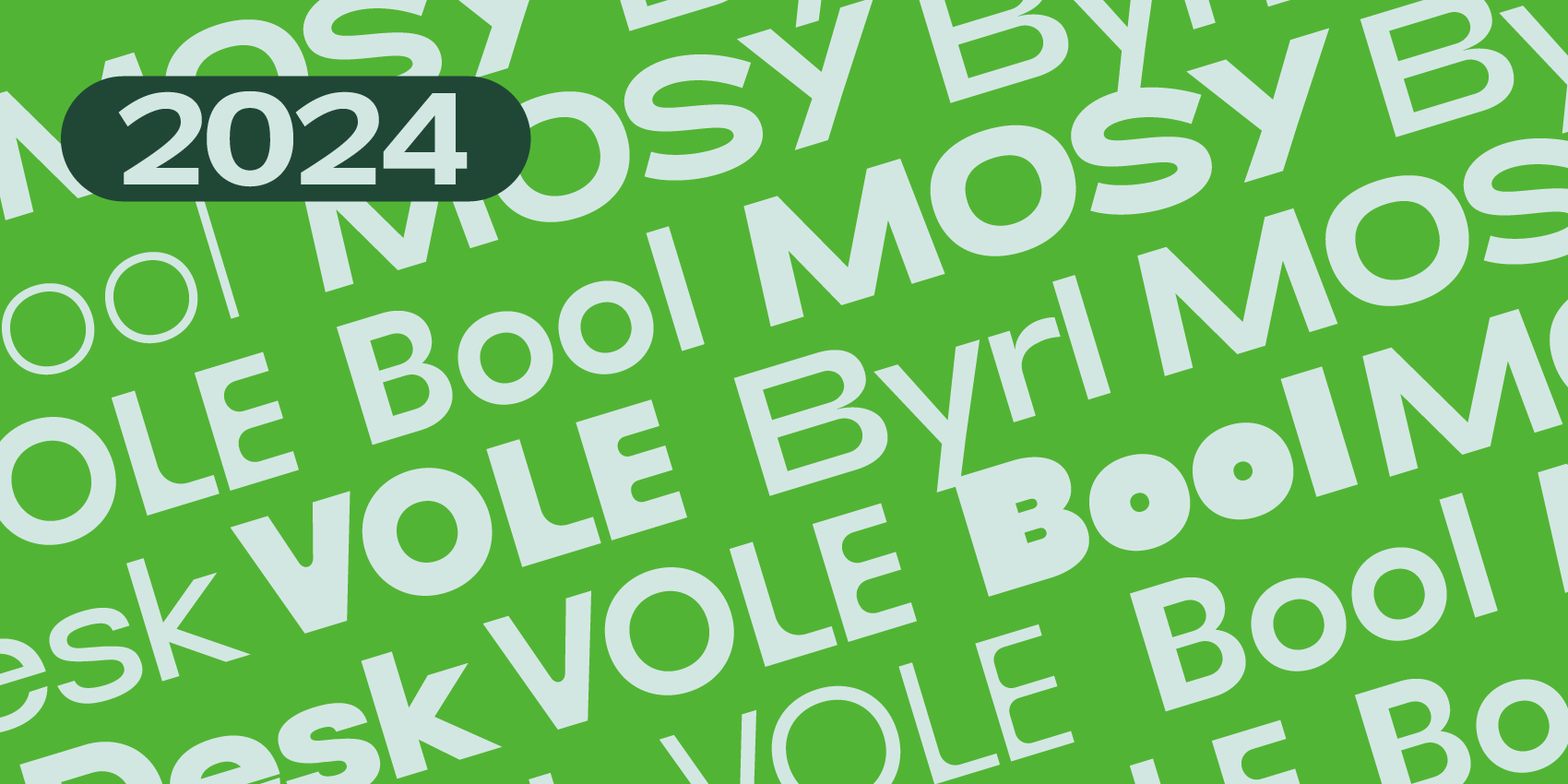
El auge de las fuentes sans-serif modernas en 2024: desde las sans simples hasta las elegantes
En 2024, las fuentes sans-serif modernas han pasado de ser minimalistas y prácticas a convertirse en una opción de estilo intencional. Las fuentes sans-serif, que no tienen los pequeños pies al final de las letras como las fuentes serif, son conocidas por su apariencia limpia y simple.
Lo que hace que las fuentes sans-serif sean modernas son características como un marco geométrico, un grosor de línea uniforme y detalles creativos que aportan personalidad: piense en letras con giros únicos como una letra S invertida o terminales extralargas (finales de un trazo) que llegan más lejos de lo habitual. Estas fuentes no solo se centran en la apariencia, sino en añadir carácter al texto.
Por otro lado, las fuentes sans-serif clásicas tienen un estilo más atemporal. Suelen ser un poco más estrechas y pueden mantener un aspecto más bien tradicional con un poco de contraste de líneas, especialmente cuando se trata de fuentes de texto.
Las fuentes retro siguen principios de diseño distintivos que prevalecen en esas épocas específicas. Por ejemplo, una fuente Bauhaus se simplifica y se construye a partir de formas geométricas. O bien, una tipografía Art Deco juega con el contraste de algunas letras que son geométricas y otras que son estrechas (condensadas). Las barras transversales pueden ser más altas o más bajas que en los diseños sans clásicos.
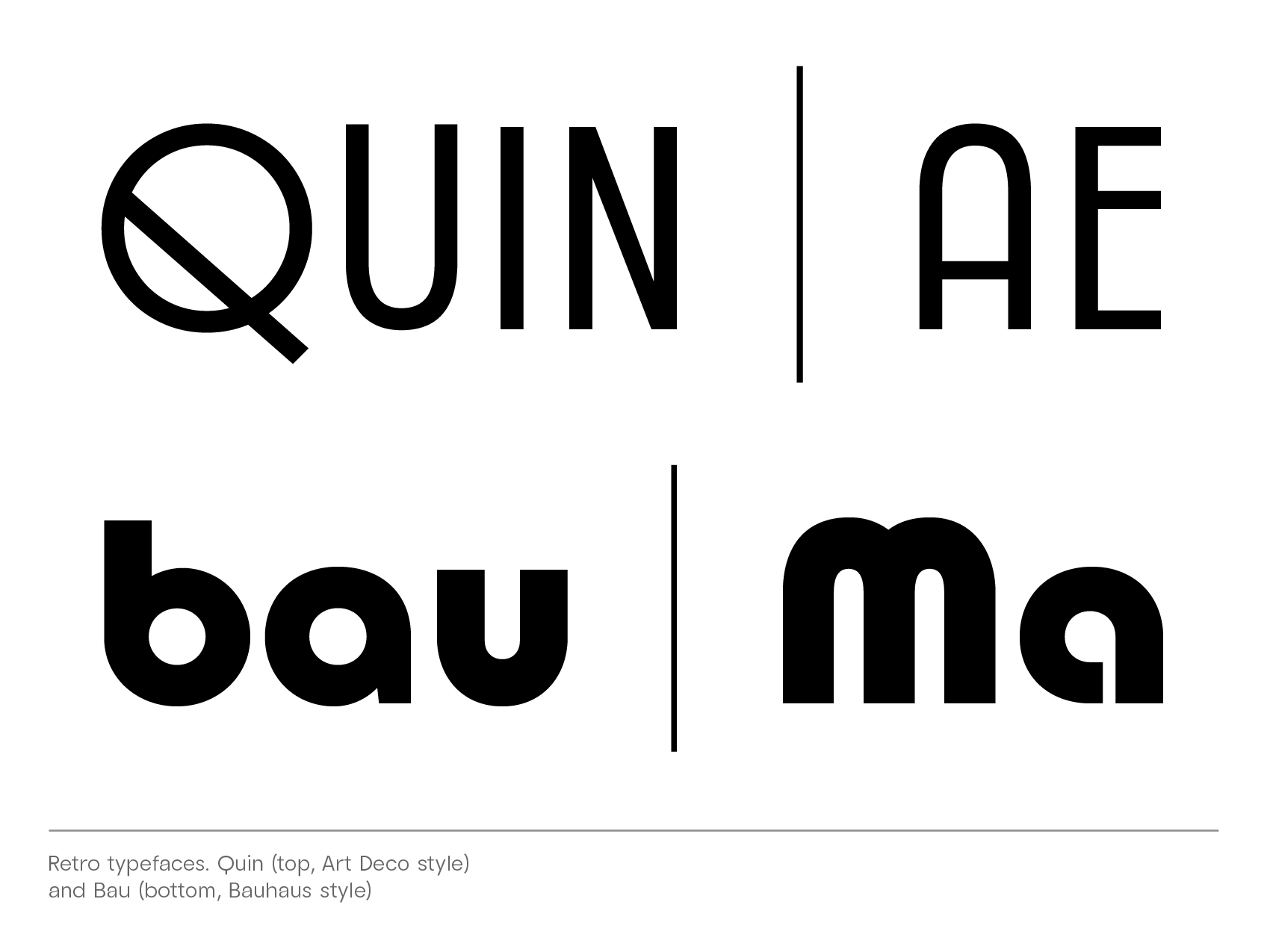
Si bien las fuentes sans-serif modernas llaman la atención ya sea por su enfoque minimalista o por su individualidad, las tipografías clásicas encajan perfectamente en cualquier punto intermedio, priorizando la facilidad de lectura.
Nuestras mejores selecciones: fuentes sans-serif modernas de nuestra colección
Acme, una fuente sans-serif genial para presentaciones y texto
Bool, fuente sans-serif divertida
Byrl, fuente sans-serif ancha (extendida)
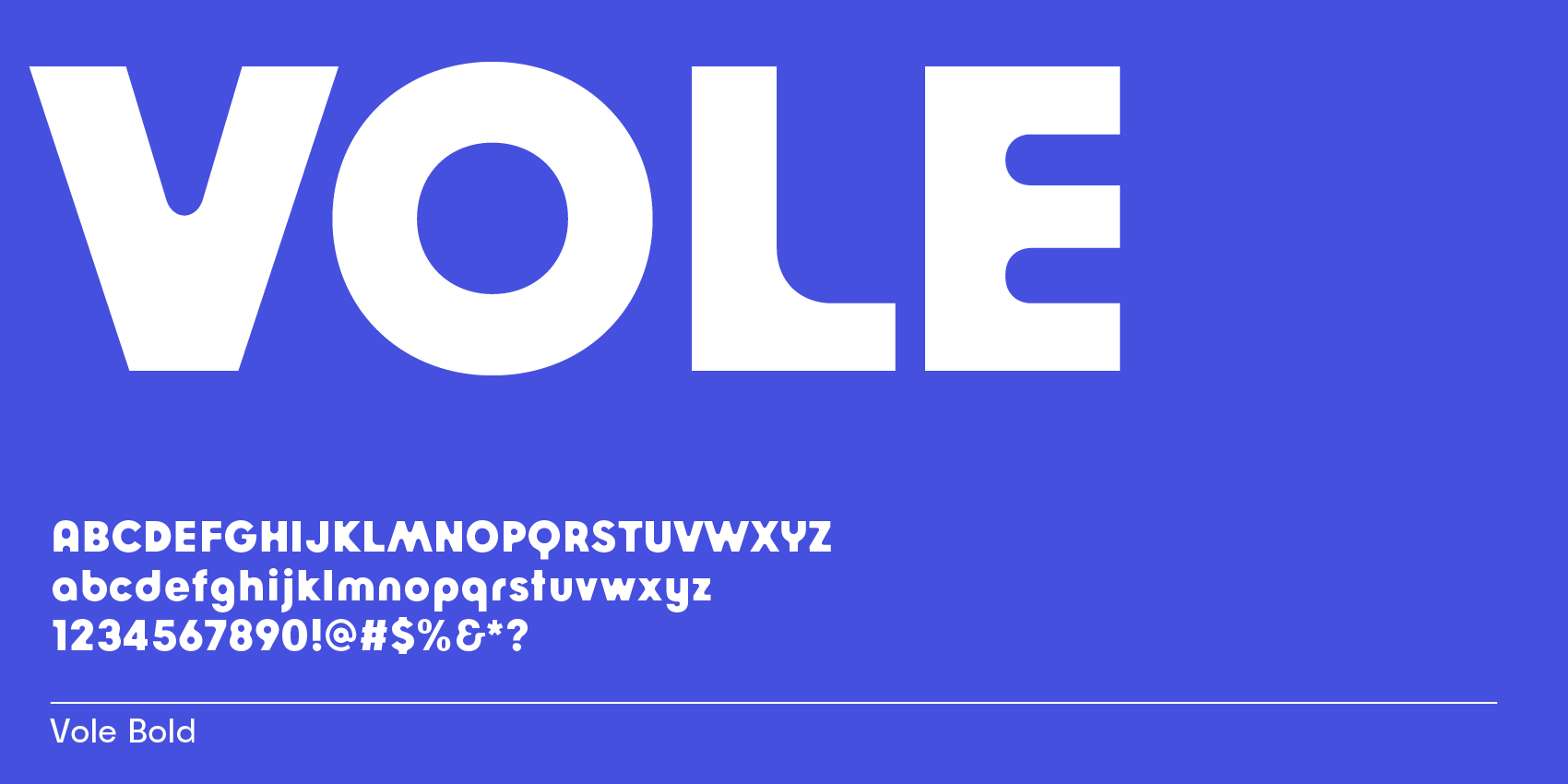
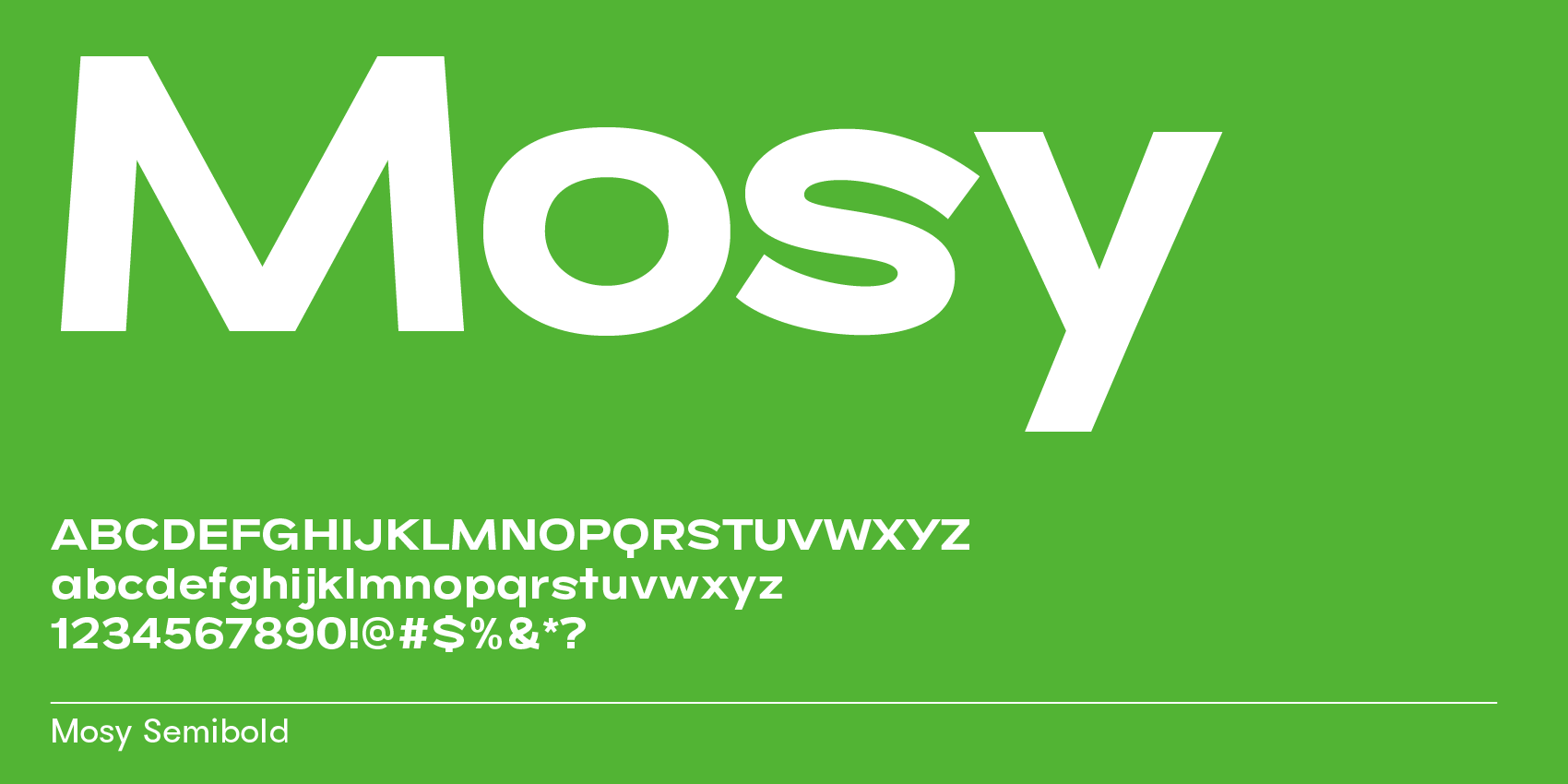
Mosy, una fuente sans-serif moderna y amigable
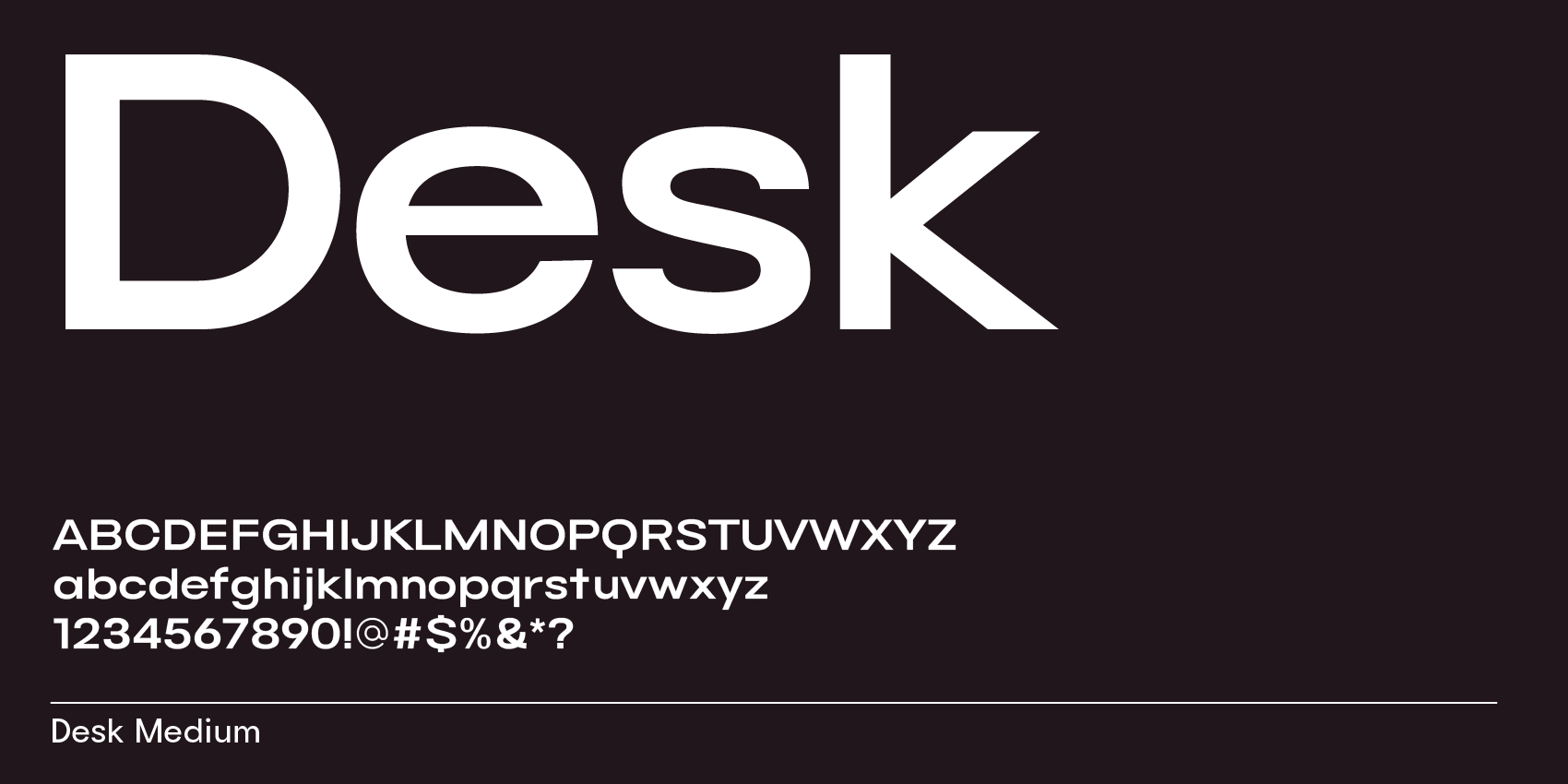
Escritorio, fuente extendida para tecnología y diseño.
Refuerza tu diseño sin coste: las mejores fuentes sans-serif gratuitas de Google Fonts
Si bien hay un puñado de fuentes sans-serif en Google Fonts que son muy populares y tienen un toque moderno (piense en Poppins y DM Sans), tener solo un marco geométrico ya no hace que una fuente sea moderna en 2024. En cambio, estamos apuntando a la tendencia del maximalismo en el diseño y estamos buscando carácter adicional dentro del diseño tipográfico.
Aquí está nuestra lista de las 5 mejores fuentes sans-serif modernas gratuitas en Google Fonts, desde las más modernas hasta las más elegantes:
1. Sin límites
Esta fuente es alargada y rompe sus trazos como líneas decorativas de punta ancha con un toque de carácter escrito a mano.
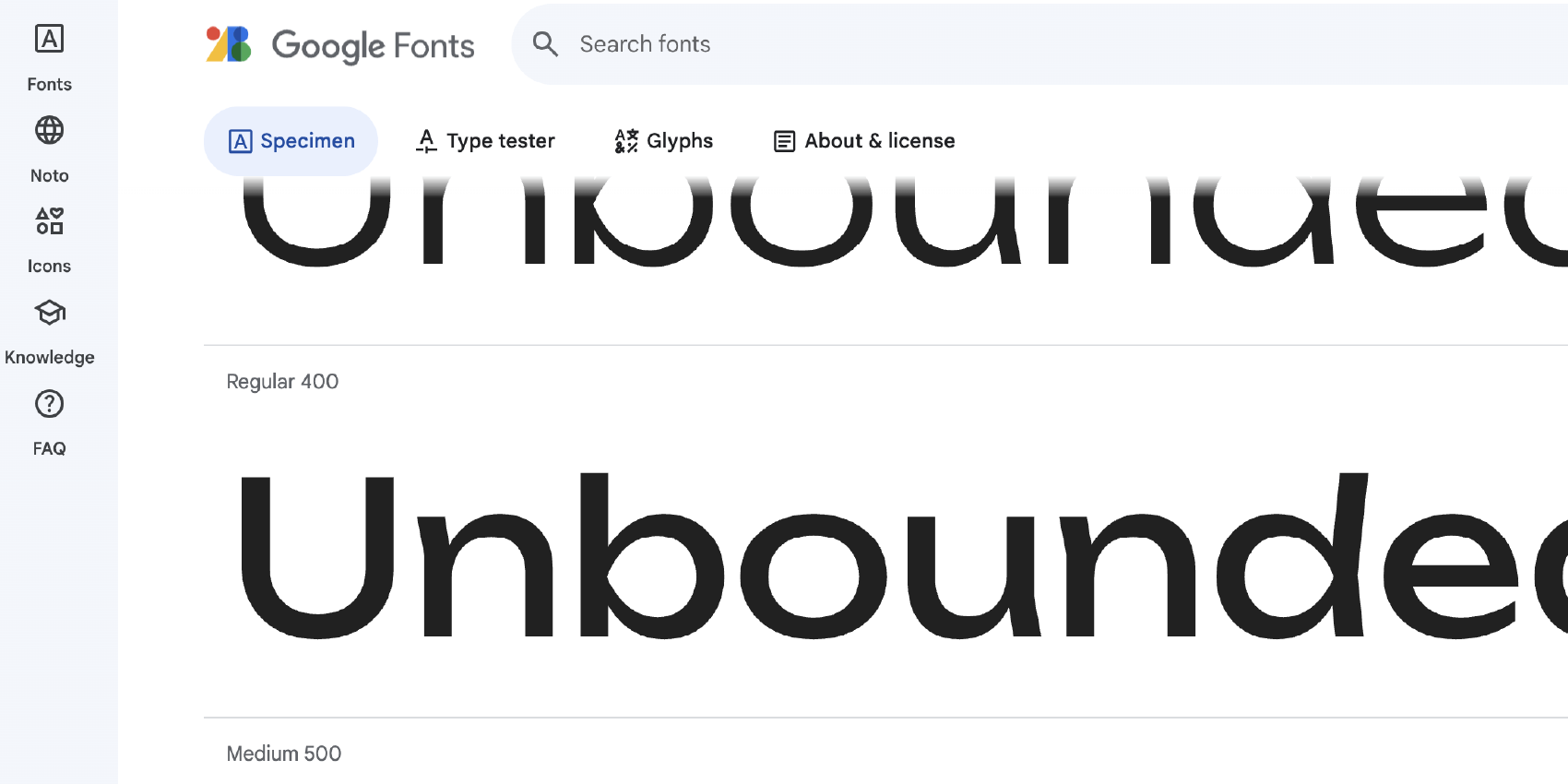
2. Bricolaje grotesco
Esta tipografía pone las trampas de tinta en primer plano. Tiene un aire de escritura a mano y terminales amigables con una mordida hacia abajo para las letras e y s.
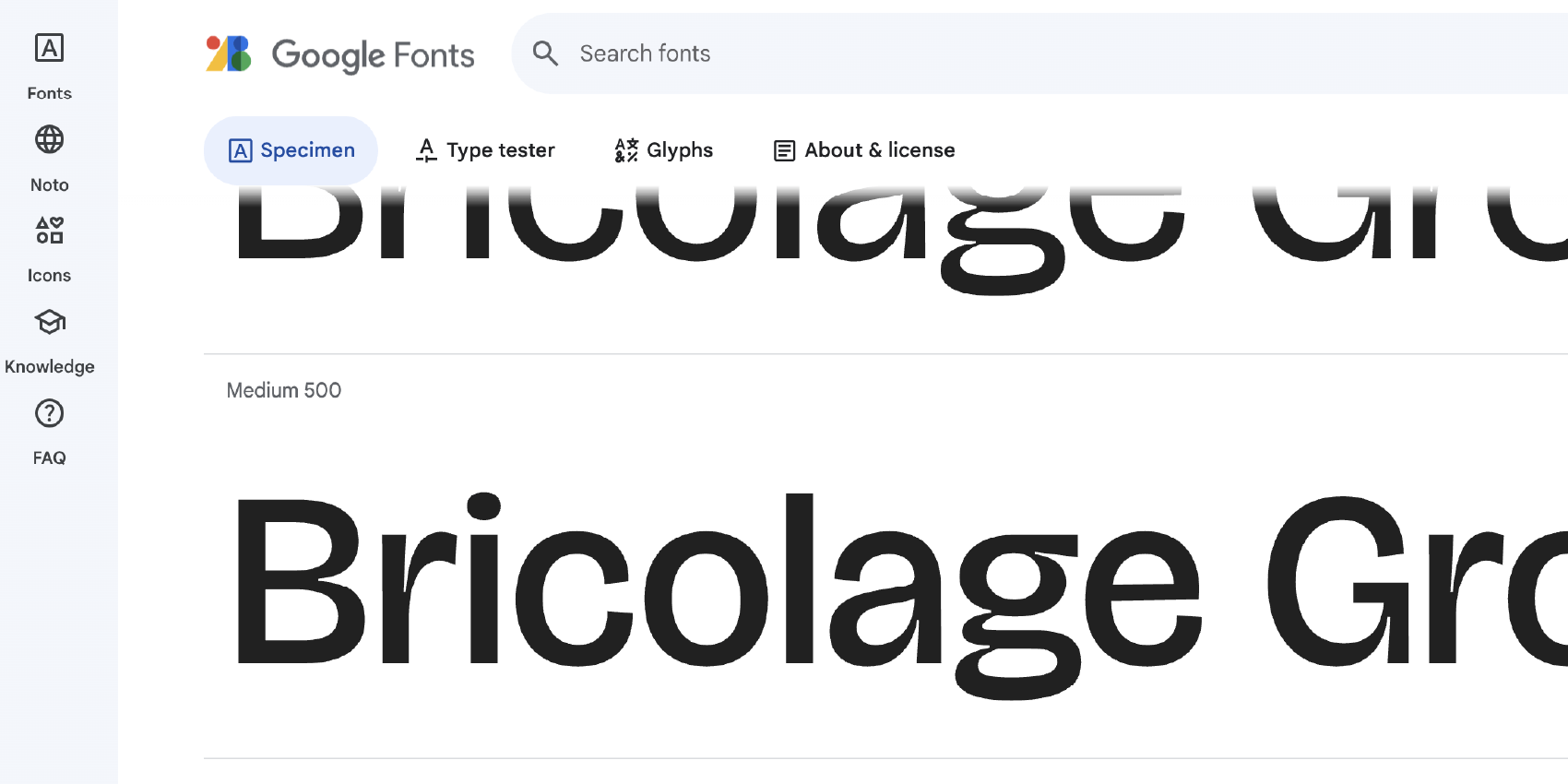
3. Grotesco espacial
La letra s está inclinada hacia atrás, las letras a, g, r y t son cuadradas, y los vértices de V y W están desplazados horizontalmente, lo que añade una sensación peculiar y más tecnológica.
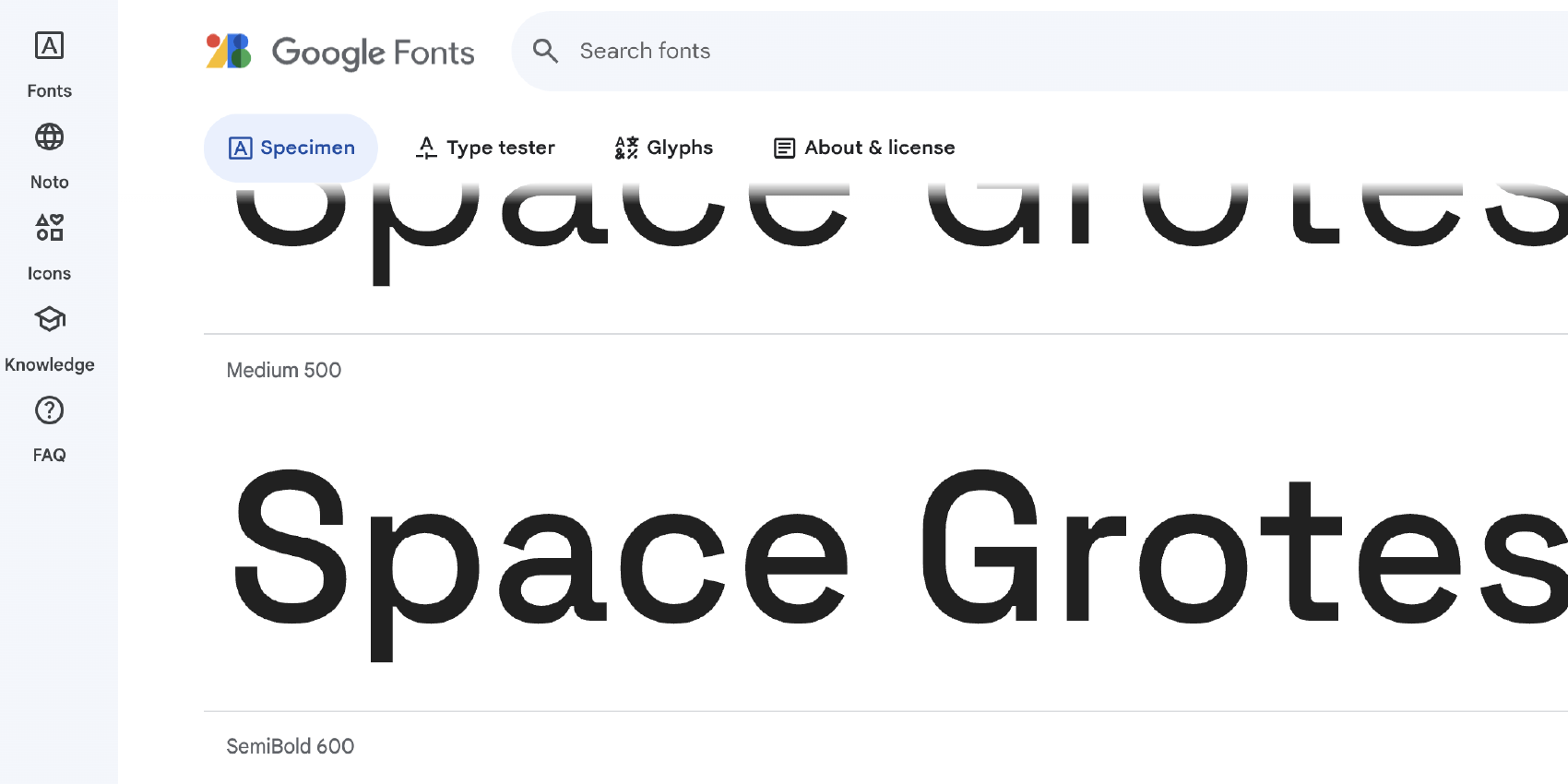
4. Plus Jakarta Sans
Esta fuente adquiere su carácter por ser un poco extraña, tal vez a propósito o por accidente. La letra s está ligeramente inclinada, el ascendente de la letra t está relleno y la letra c está cortada en diagonal, lo que le suma un toque moderno a esta fuente sin serifa.
5. Exhibición “Madefor” de Wix
Similar a Gotham, conocida como la fuente Obama, Wix “Madefor” Display utiliza un estilo muy geométrico pero con un arco en forma de f cuadrado y una s mínimamente peculiar con su lomo sobresaliendo ligeramente.